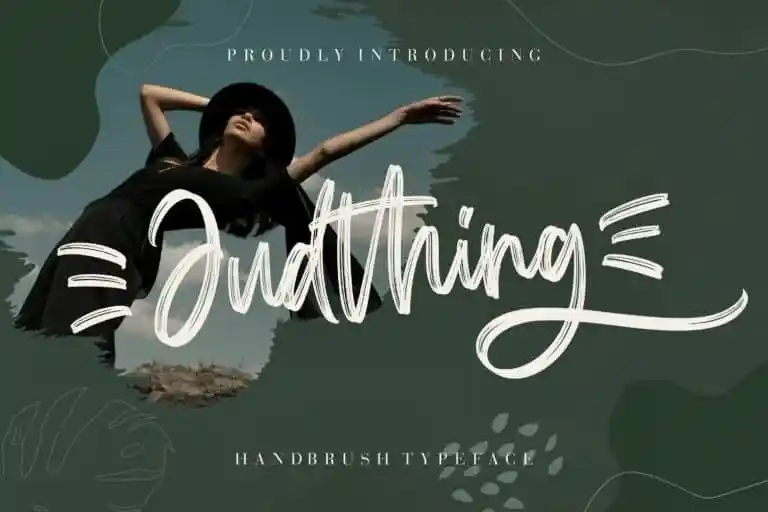
Judthing Brush Font – Download Grátis
Judthing Brush Font é uma elegante e vibrante fonte que se destaca no mundo dos escripts. Desenvolvida por 99designs, ela incorpora elementos tanto estilizados quanto despojados, resultando num ar inconfundivelmente charmoso e atemporal. Suas linhas sofisticadas brincam com o estilo feminino de uma maneira ligeiramente travessa, combinando-se perfeitamente em projetos que valorizam tanto a criatividade quanto a delicadeza. Ideal para designers buscando dar um toque único e fashionista aos seus trabalhos, Judthing Brush Font é como um livro de recado pessoal, onde cada letra carrega consigo uma história emocionante de amor e cuidado. Combinada com outros recursos gráficos, ela cria projetos que fluem naturalmente e se destacam em qualquer projeto visual.